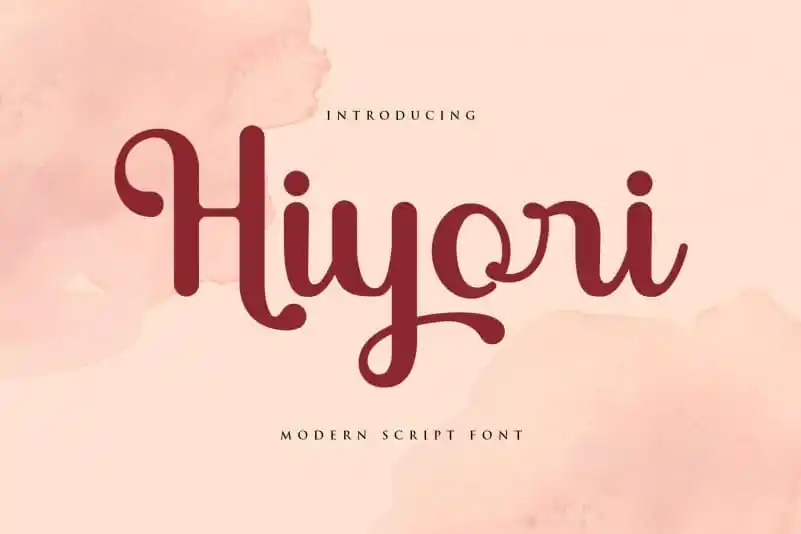
Hiyori Script Font – Download Grátis
Introduzimos Hiyori Script Font, uma elegante e bela fonte de escrita manuscrita moderna cuidadosamente elaborada para se tornar um verdadeiro favorito. Sua calma casual faz dela aparentemente muito tranquila, leitorável e, finalmente, extremamente versátil. Hiyori oferece mais alternativas com o início do swash e o fim do swash, sendo uma escolha excelente para água-marinhas em organizadores de casamentos, assinaturas ou logos de assinatura, frases, capas de álbuns e muitos outros projetos de design. Hiyori está aqui para levar seu trabalho ou sua empresa a um nível superior!